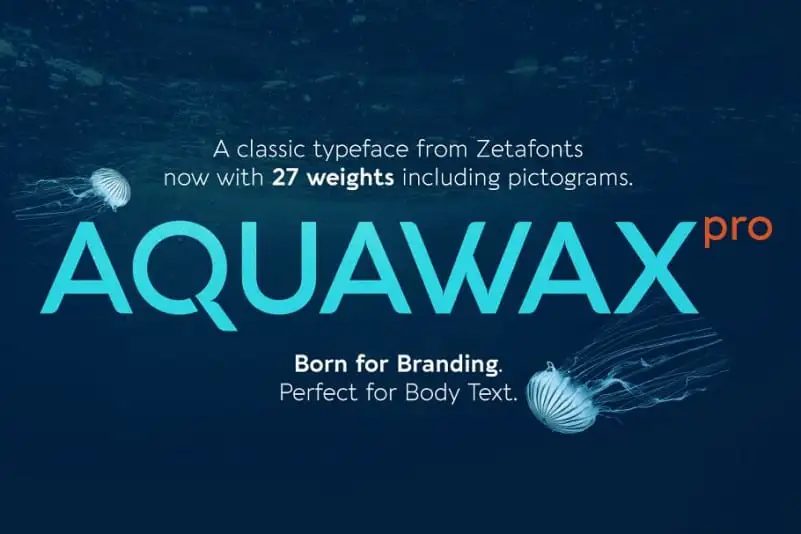
Descobrimos uma nova família de fuentes que vale a pena explorar: Aquawax Pro Font Family. Criada pelo designer italiano Francesco Canovaro, essa família foi desenvolvida como um tipo personalizado para uso empresarial e revela seus originais traços em projetos visuais como o logotipo da Warner Bros para sua mais nova atração cinematográfica: Aquaman. Os detalhes criativos incluem uma cauda afiada no ‘Q’ e uma asa fina na direita do ‘K’. A tipografia também incorpora um desenho invertido dos caracteres ‘W’, além de bordas arredondadas que dão ao tipo uma aparência levemente mais suave. Apesar desses detalhes, a família manteria sua estética modernista e geometricamente perfeita. Apesar das características visuais complexas, a família é extremamente legível em formatos menores, tornando-a ideal para uso em textos corporativos ou websites. Essa fórmula faz com que Aquawax Pro seja um recurso de fontes perfeito tanto para projetos de marca quanto para qualquer tipo de conteúdo digital onde leitura rápida e clara sejam essenciais.